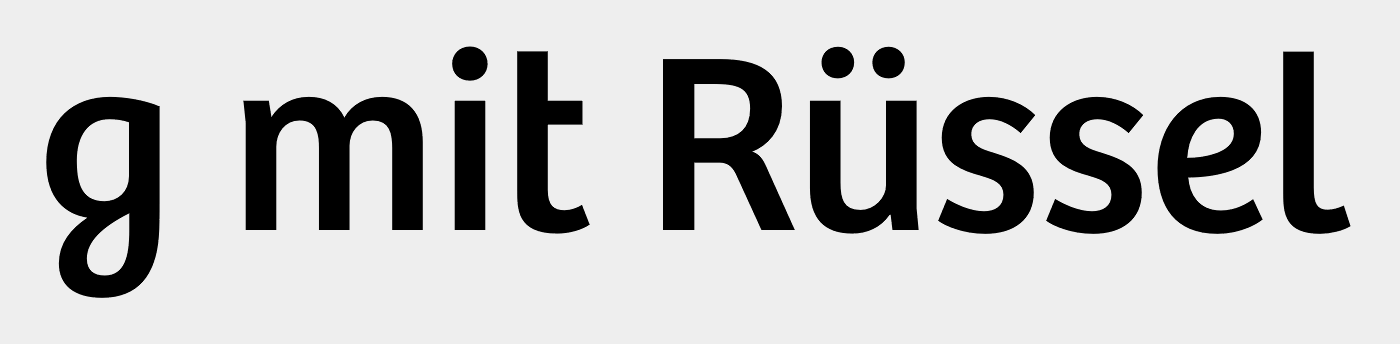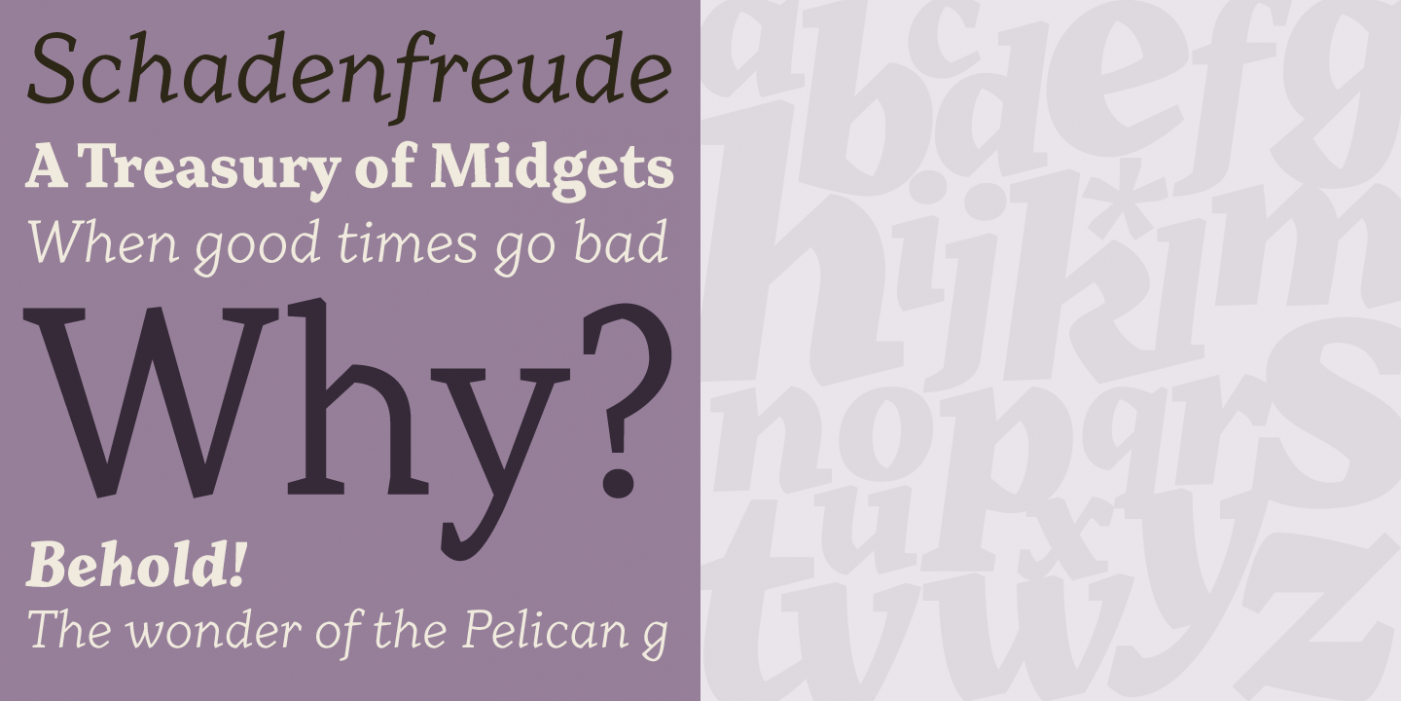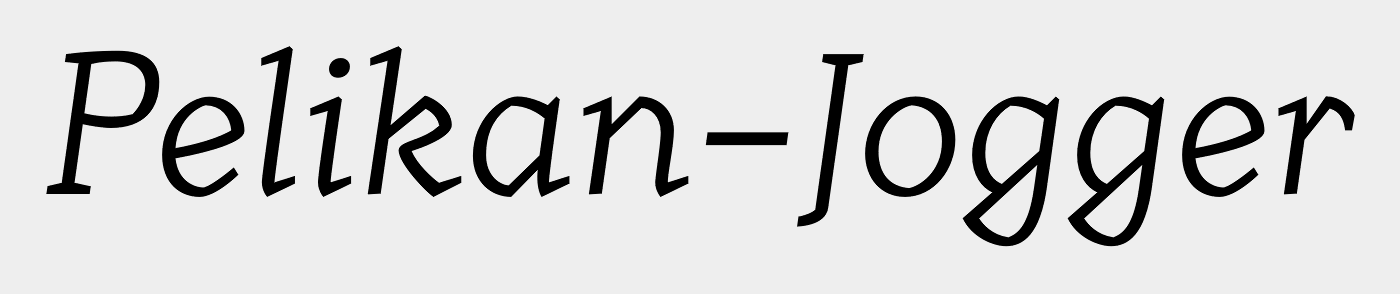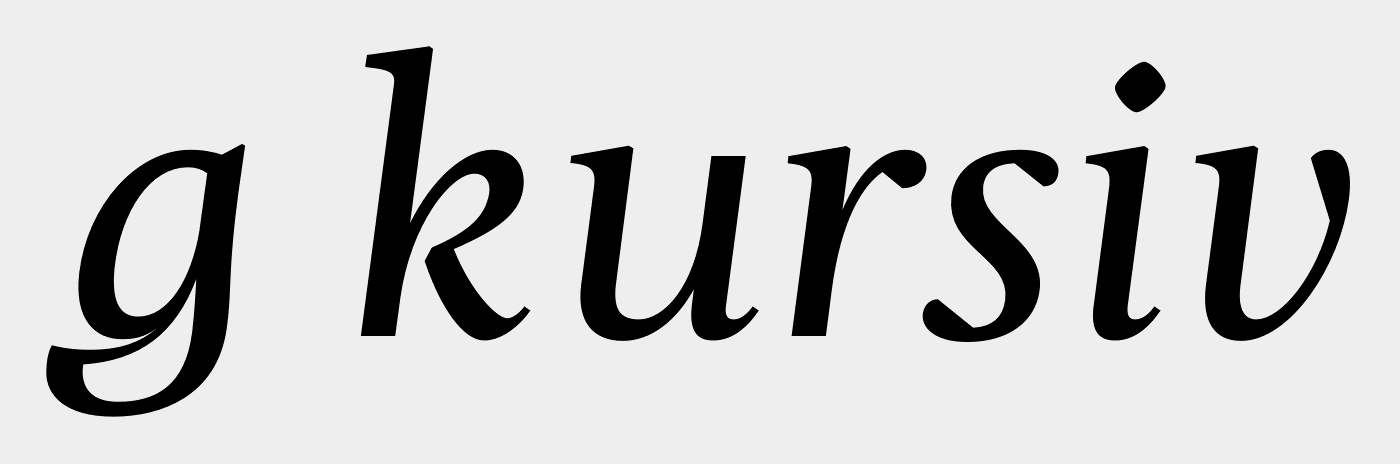
Das Elefanten-g oder …?
Eine geschätzte Kollegin im Forum hat für folgende g-Form aufgrund der Assoziationsmöglichkeiten den schönen Begriff »Elefanten-g« geprägt.
Mich würde nun interessieren, ob man das in der Fachwelt noch anders nennt – zum Beispiel g mit kalligrafischer Schlaufe o. ä. Hat jemand eine Idee?
Hmm, hatte ich auch schon drüber nachgedacht. Aber ich sag mal beim aufrechten Antiqua-g wie bei der Tisa hier ist die Verbindung zwischen ersten und zweiten Stock? auf der linken Seite, beim Beispiel oben aber rechts. Und die »Zwischenplattform vom Treppenhaus« fehlt auch irgendwie, da die untere Schlaufe quasi unmittelbar den oberen Stock berührt.
Mir kommt das Elefanten-g eher so vor, als wäre es von der Schreibschrift-Form abgeleitet. Liegt ja auch nahe bei einer aufrechten Kursiven wie der Bree. Aber man findet es ja genauso auch in echten Kursiven wie bei der Christel:
Von daher weiß ich nicht, ob man hierfür auch eine neue Schublade aufmachen könnte/sollte/…
Im Grunde ist es ja ein reguläres zweistöckiges g, wie wir das hier nennen.
Tschuldige, habe Dich wohl missverstanden. Du hattest die ganze Zeit sicher schon das rechte vor Augen, wo ich jetzt noch bei der linken Form war:
Dann wäre der Unterschied natürlich lediglich, dass die Unterlänge geschlossen ist.
Also zweistöckiges g mit geschlossener Unterlänge? :-?
Elefanten-g
Besser lässt sich diese g-Form nicht beschreiben. Isso™. :baeh:
Ach, da wär’ ich eher für elephant g. Immerhin ist da ja nicht nur ein Rüssel zu sehen, sondern der ganze Elefantenkopf mit Rüssel. Außerdem ist trunk mehrdeutig, da könnte man auch nach einer kistenförmigen g-Form suchen.
Der Ausdruck ist mir entweder bei Typophile oder bei Typedrawers zuerst ins Auge gefallen, wenn ich mich recht entsinne. Vielleicht sogar bei beiden. Jetzt auf die Schnelle konnte ich die entsprechenden Beiträge aber nicht mehr finden.
Eine der Beispielgrafiken zur oben verlinkten Range Serif enthält den Begriff übrigens auch und stammt von 2012 – die Forenbeiträge, an die ich denke, müssten hingegen mit hoher Wahrscheinlichkeit später entstanden sein. Mit einer früheren Nennung als der von 2012 kann ich nicht aufwarten …
Zumindest bei t, k und ß hätten die das auch noch durchziehen können 8-)
... zumal k mit Schlaufe oben ja nix außergewöhnliches wäre und daher prädestiniert wäre, mitzurüsseln ...